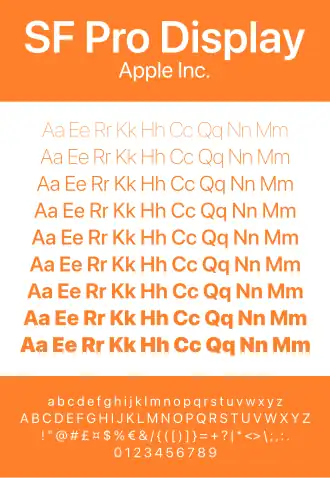
San Francisco (гарнитура)
| Стиль | без засечек |
| Классификация | векторный |
| Дата создания | 2015 |
| Дизайнер | Apple Inc. |
| Набор символов | Юникод |
San Francisco — шрифтовая гарнитура типа новый гротеск, созданная компанией Apple. Была впервые представлена для разработчиков 18 ноября 2014 года[1][2]. Сперва использовался как системный шрифт Apple Watch, а позднее заменил и Helvetica Neue в MacOS и iOS, начиная с OS X El Capitan и iOS 9[3][4][5]. San Francisco также стал системным шрифтом для tvOS, начиная с 4-го поколения Apple TV[6]. Это первый новый шрифт, разработанный в Apple за последние почти 20 лет[1].
Варианты
San Francisco имеет два варианта: «SF» для MacOS, iOS и tvOS; и «SF compact» для WatchOS[4]. Основное отличие заключается в том, что боковые стенки букв с круглыми формами, такие как о, е, и s, — круглые в SF, тогда как в SF compact они плоские. Благодаря плоским боковым стенкам литер пространство между ними становится больше, тем самым делая текст более разборчивым в малых кеглях, что особенно важно для Apple Watch[7]. Оба шрифта имеют два оптических размера: заголовочный для крупного текста и текстовый для мелкого. По сравнению с заголовочным буквы в текстовом начертании имеют больший внутрибуквенный просвет и более щедрый межбуквенный интервал (трекинг). Операционная система автоматически выбирает заголовочный вариант для размеров не менее 20 пунктов и текстовый для остальных[7].
Шрифт лицензирован для зарегистрированных сторонних разработчиков для проектирования и разработки приложений для watchOS, tvOS, macOS и iOS. Он также используется на MacBook начиная с 2015 года как шрифт на клавиатуре (взамен VAG Rounded[8]).